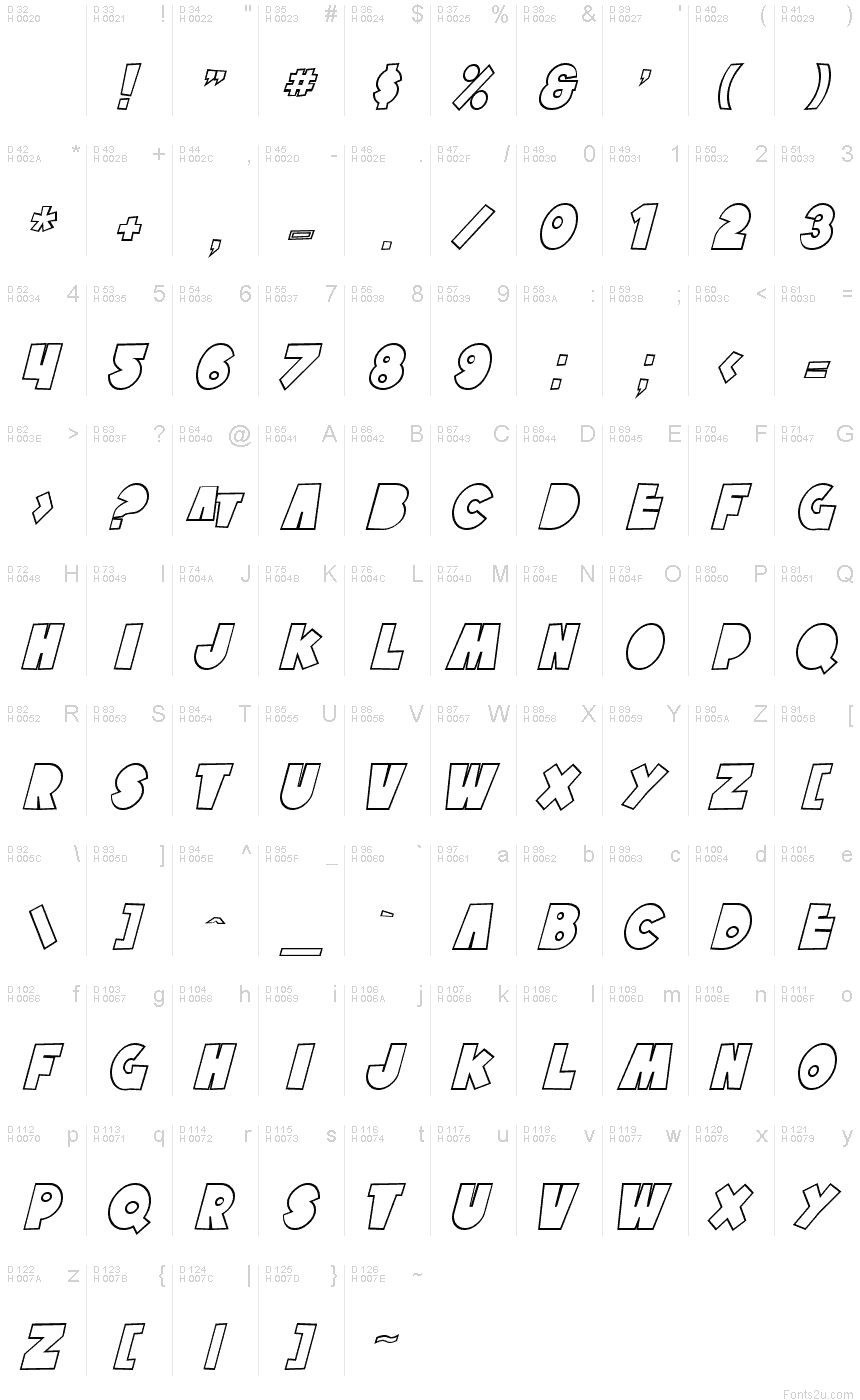
SF Tattle Tales Outline Italic von ShyFoundry ist eine kostenlose, kursive Display-Schrift im Comic-Outline-Stil, die den Schwung und die Energie alter Kinder-Comics versprüht. Die Buchstaben wirken breit und lebendig; sie bestehen aus kräftigen Umrissen und erhalten durch ihre starke Neigung eine verspielte, dynamische Note, die selbst kurzen Wörtern sofort Charakter verleiht.
Sie eignet sich hervorragend für Comic-Überschriften, Branding im Stile von Cornflakes-Packungen, Party-Flyer, Titelkarten oder markante Cover-Zeilen – überall dort, wo ein auffälliger Retro-Look gefragt ist. Als kostenlose Schrift bietet sie sich auch wunderbar für Monogramme oder Initialen an, da der Outline-Stil viel Freiraum lässt und die Cartoon-Energie leichtfüßig statt schwerfällig wirken lässt.